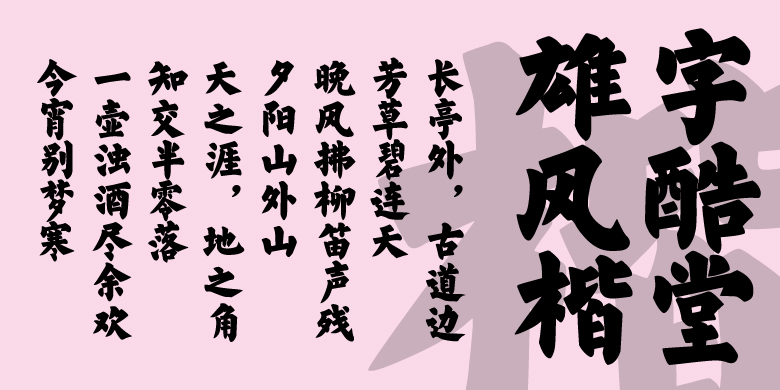
字酷堂雄风楷
字酷堂雄风楷,字体风格源于柳公权,同时融合了颜真卿楷书雄浑的特点。笔划舒展,结体严谨,中宫收紧,字形挺拔。 柳公权,唐朝中期书法家。工于辞赋,擅长书法。其书初学王羲之,遍观唐代名家书法,吸取了颜真卿、欧阳询之长,溶汇新意,自创独树一帜的“柳体”,以骨力劲健见长,与颜真卿齐名,人称“颜柳”,后世有“颜筋柳骨”的美誉。以楷书著称,与欧阳询、颜真卿、赵孟頫并称“楷书四大家”。代表作有《金刚经刻石》《玄秘塔碑》《神策军碑》等。